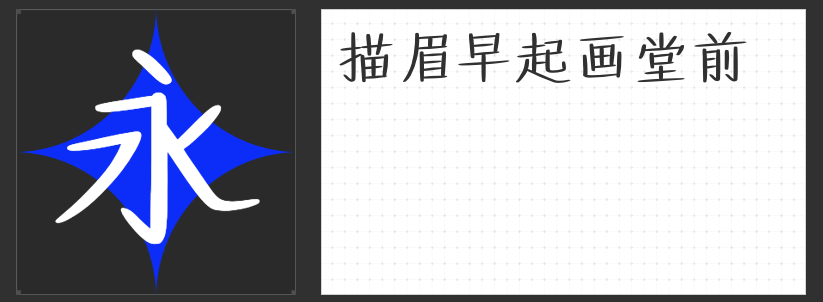
四款影视级字体:重构视觉叙事的文字美学方案
在影视设计的视觉语言体系中,字体不仅是信息载体,更是情绪催化剂与风格定调者。本文精选四款各具张力的专业字体,为片头字幕、概念海报、动态图形等场景提供多维度的美学解决方案。
一、励字钧线黑简 微黑
以精密斜度切割视觉空间,这款全直线设计的字体构建出机械美学的秩序感。其棱角分明的转折系统,在科幻题材中可强化科技产品的冰冷质感,而在悬疑片头中则能通过锐利笔触传递紧张氛围。设计师通过微米级笔划优化,在保持视觉冲击力的同时,确保4K屏幕下的可读性,使长标题序列保持呼吸节奏。
二、字恋狂嗨玩简
突破常规字重比例的积木式结构,赋予文字玩具般的可触摸质感。重心下沉的设计语言,在动画电影海报中可营造稳定感,而夸张的负形空间则为动态设计预留了变形轨道。这款字体的"不完美"轮廓,恰好契合独立电影对打破常规的审美追求,尤其适合作为青年文化题材的视觉符号。
三、励字超级勇士简 常规
将黑体的严谨骨架与几何化的现代笔触融合,创造出兼具理性与温度的中间字体。适中的字面率使其在历史剧字幕中保持庄重,而柔和的圆角处理又消解了传统黑体的严肃感。这款字体的秘密在于"隐形设计"——通过光学补偿技术,让不同字号的文字在运动镜头中始终保持视觉重心稳定。
四、字圈也字画眉楷书
在保留楷书基因的同时,这款字体通过笔划粗细的微调,构建出适合长文本阅读的现代韵律。其方正结构暗合网格系统设计原则,而略带弧度的收笔又为严肃题材注入人文气息。在纪录片字幕或古装剧片尾中,画眉楷书能以克制的姿态完成文化叙事的转场。
这四款字体通过不同的设计哲学,重新定义了文字在影视时空中的存在方式——从未来感的几何切割到童趣的形态解构,从古典韵律的现代表达到叙事媒介的温度传递,为视觉创作者提供了超越工具属性的美学选择。